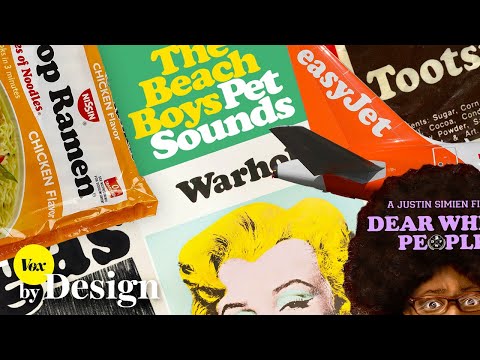
Wieso die Schriftart "Cooper Black" überall zu sehen ist cooper-black-font-ueberall
Steven Heller und Bethany Heck haben für Vox über eine Schriftart gesprochen, die „überall“ zu sehen ist: Cooper Black. Ist mir im allgemeinen Alltag jetzt noch nicht in der Hülle aufgefallen, aber da werde ich in Zukunft definitiv verstärkt drauf achten!
„There’s a typeface that has made a resurgence in the last couple of years. It’s appeared on hip hop album covers, food packaging, and advertising. Perhaps you know it from the Garfield comics, Tootsie Roll logo, or the Pet Sounds album cover by the Beach Boys. It’s called Cooper Black, and its popularity and ubiquity has never waned in the hundred years since it was first designed.“